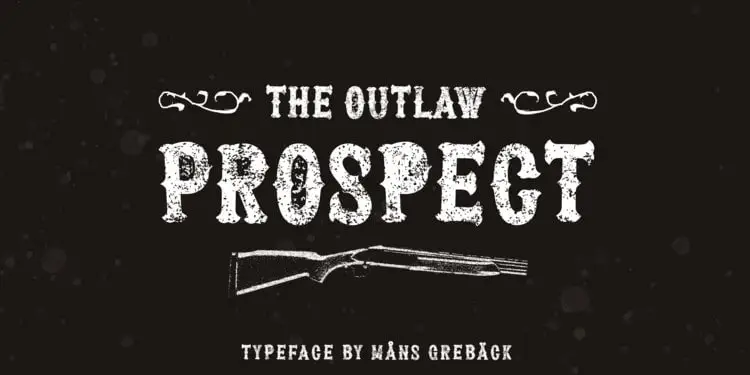
A fonte Prospect Display é uma herança clássica para etiquetas de exibição. Inspirada nos velhos modelos de embalagens e nas velhas placas de sinais, esta tipografia oferece um estilo sólido e decorativo ideal para aplicativos onde você deseja chamar a atenção do público. Com sua inspiração no design vintage, o Prospect Display Font é perfeito para adicionar uma aparência genuinamente antiga aos seus mensagens, tornando-as mais chamativas e memoráveis sem perder seu significado ou estilo moderno. Seja em cartazes de eventos, logotipos ou publicidade em outdoors, esta fonte certamente dará o toque final que você precisa para suas criações visuais.